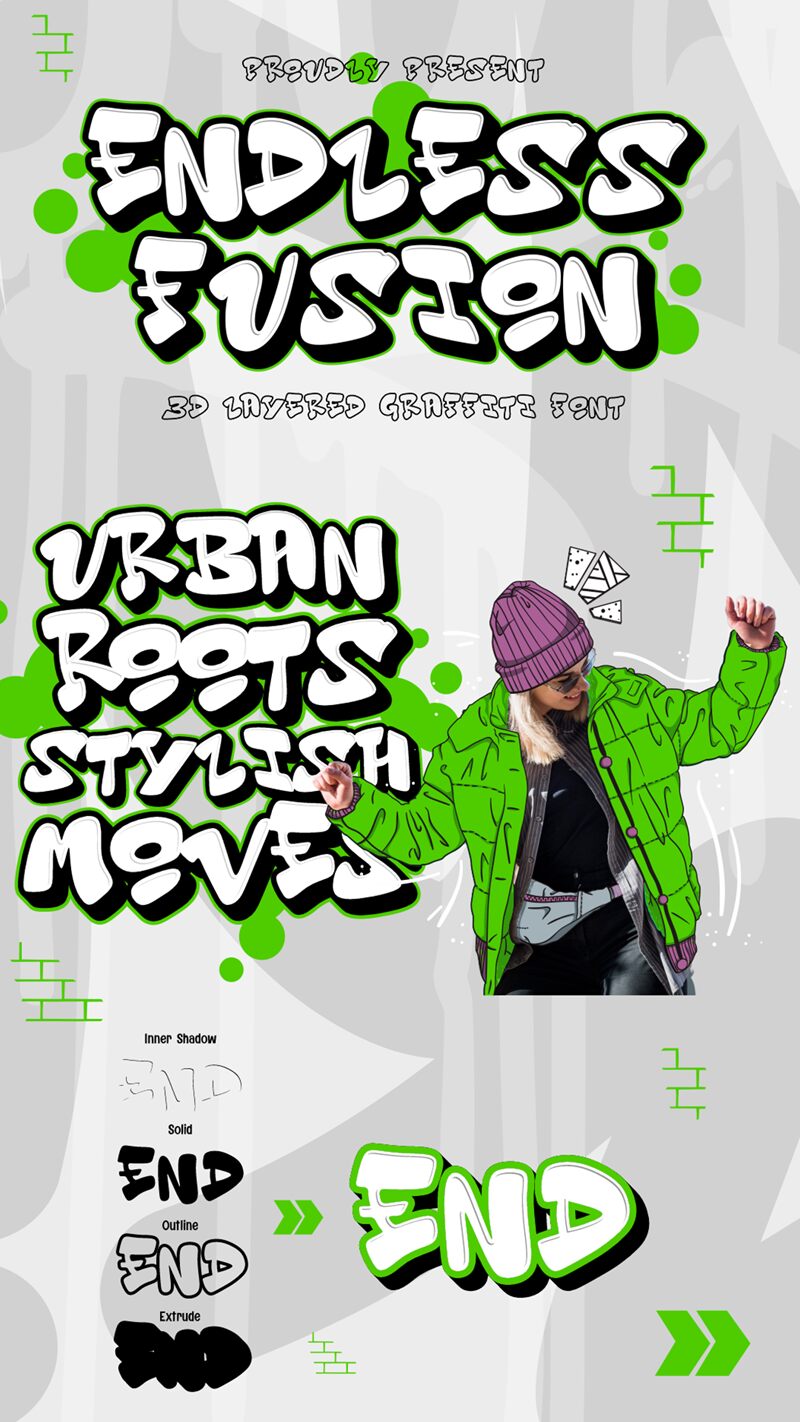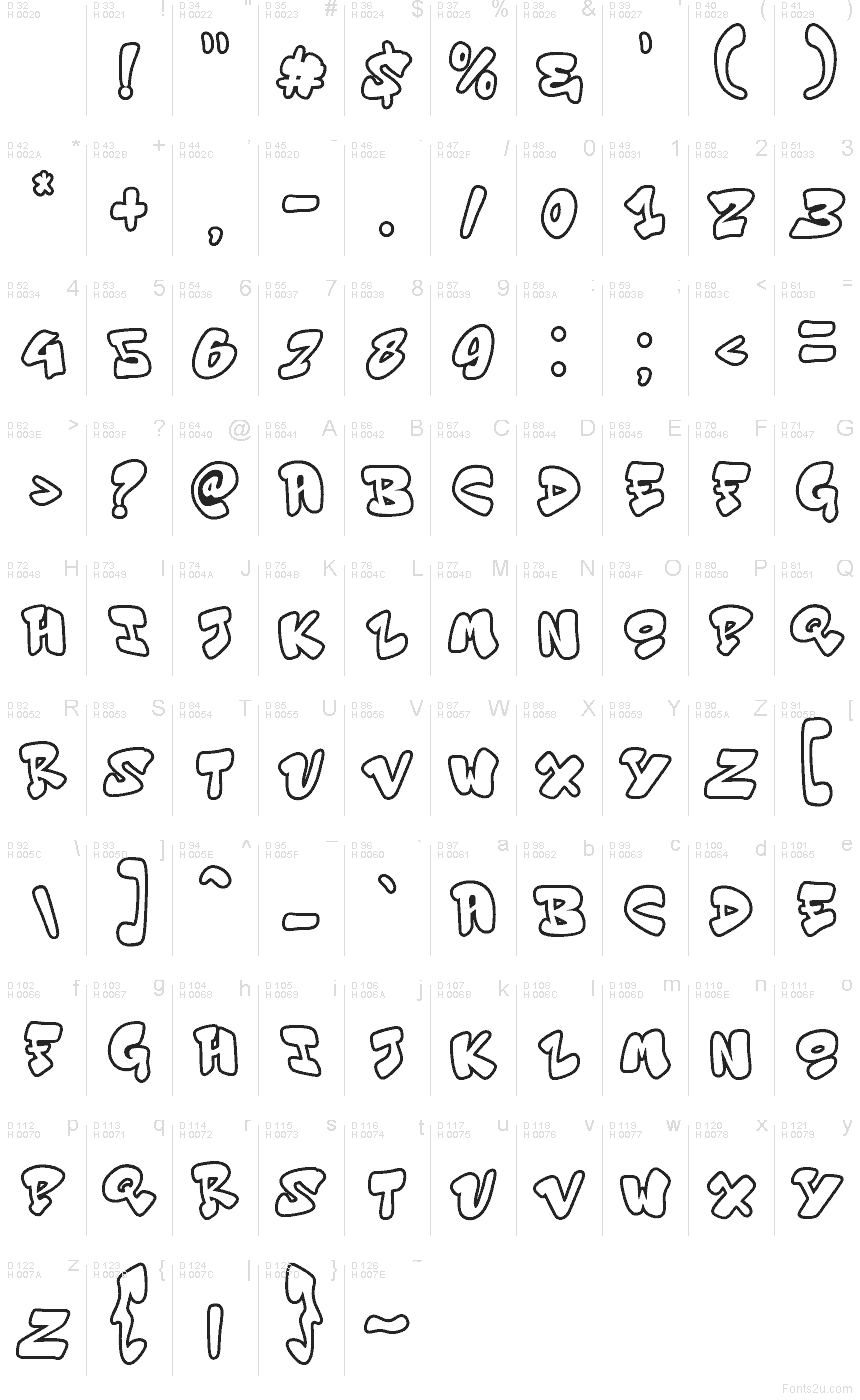
Endless Fusion Outline od Muhammada Panji Ramdhaniho z Figuree Studio je graffiti font z rodiny Endless Fusion, který nabízíme zdarma. Vyznačuje se vzdušnými obrysy a vypouklými tvary, které připomínají kresbu fixou. Díky stálému rytmu a velkorysým rozestupům působí chaoticky, ale přitom přehledně a hravě. Otevřené vnitřky písmen mu dodávají energii jako by byl načrtnutý na zeď, a přesto zůstává na první pohled překvapivě čitelný.
S Endless Fusion Outline dodáte výrazný styl logům pro streetwear, nadpisům na plakátech, grafice na skateboardy, festivalovým upoutávkám, náhledům na YouTube, samolepkám nebo hravým obalům. Nechte ho vyniknout ve velké velikosti, aby obrysy mohly dýchat, a pro doplňující texty ho zkuste kombinovat s čistým, jednoduchým bezpatkovým písmem. Tento bezplatný font také skvěle vypadá s jemným zrnem nebo texturou spreje, což umocní jeho ručně kreslený vzhled.